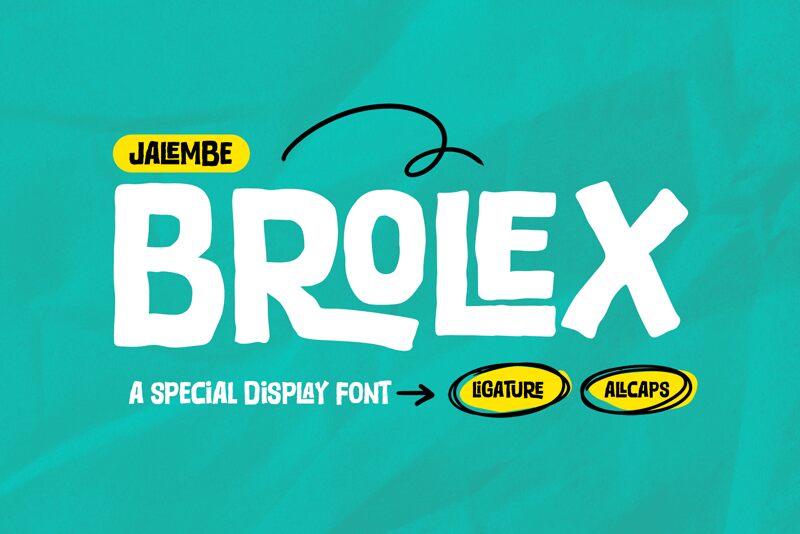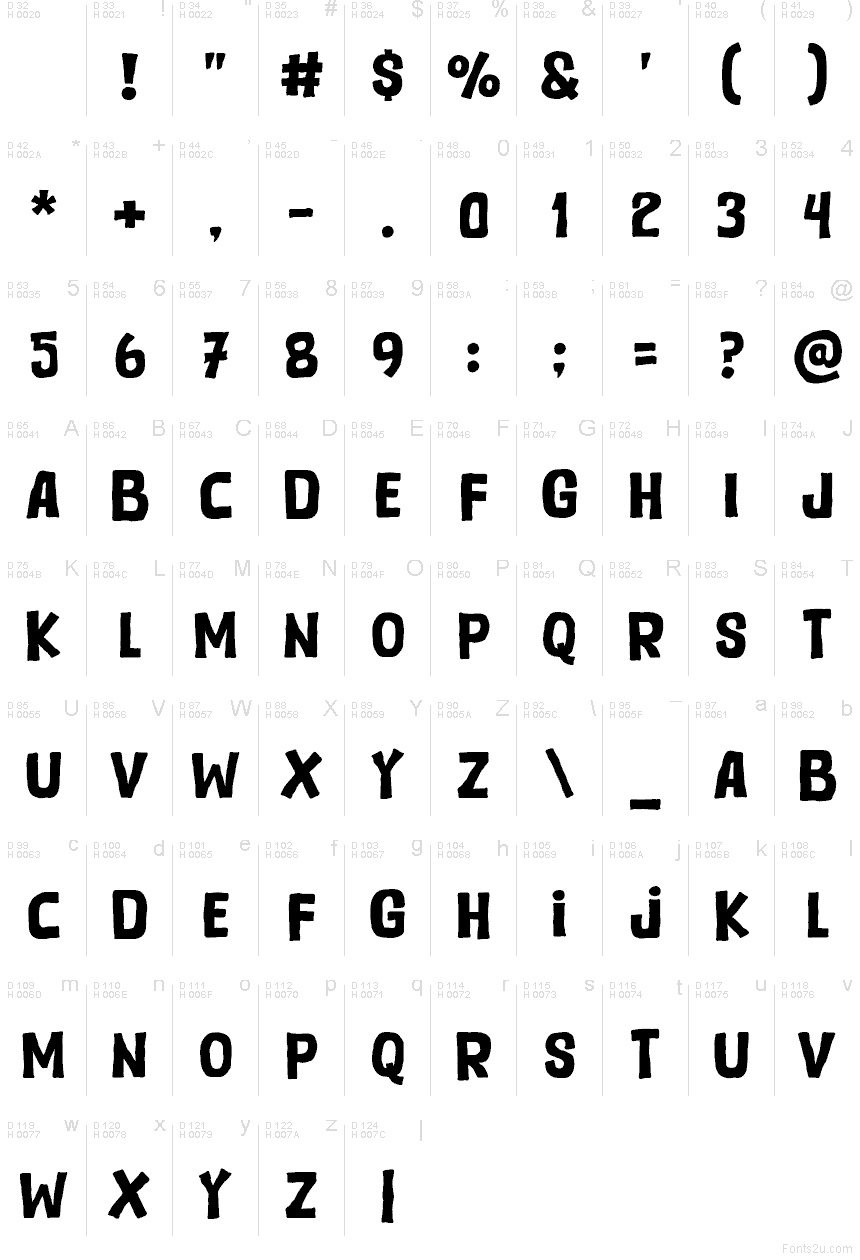
Brolex
Шрифт Brolex от Khurasan & Jalembe - это бесплатный игровой шрифт в стиле мультяшного дисплейного начертания со скругленными, неровными буквами и ощущением ручной работы. Формы широкие и слегка «плавающие», с мягкими углами и нерегулярными изгибами, что сохраняет непринужденный ритм, избегая механической жесткости.
Brolex отлично подходит для заголовков комиксов, детского брендинга, постеров, стикеров, упаковки и яркой графики для соцсетей, так как его неформальные формы обладают живым, «от руки» характером. Этот бесплатный шрифт также хорош для логотипов и обложек, когда вам нужно что-то повседневное, с выразительными контурами и легкой долей эксцентричности, но при этом аккуратное.